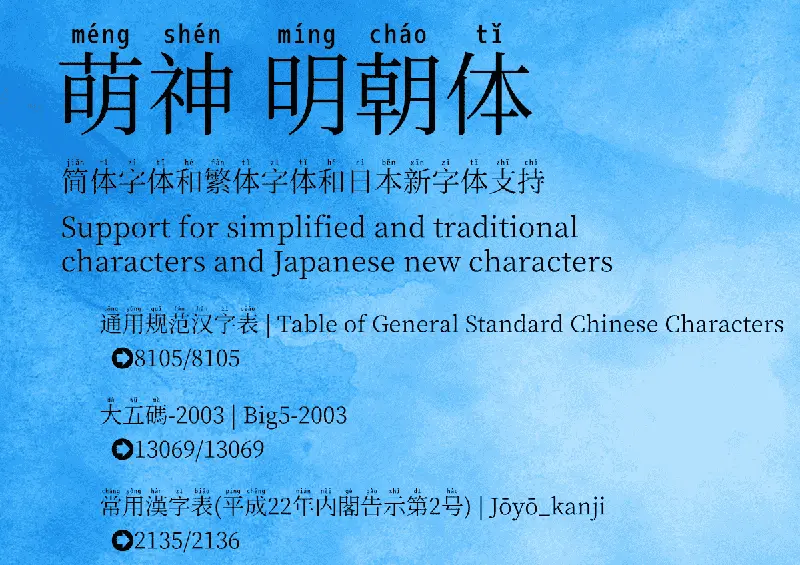
萌神拼音體是一款用於學習中國漢字的字體,由思源宋體和M+字體進行改造而成,採用SIL Open Font License 1.1授權協議發佈的一款免費商用字體。 這是一種用來幫助學生更快地學習和閱讀漢語的字體。在某些設計場景其實也挺實用的,特別是對教育類的設計比較有用。
萌神拼音體基本上是可以顯示日語、簡體字和繁體字的字體,是在簡體字和繁體字中加入拼音的字體的製作。